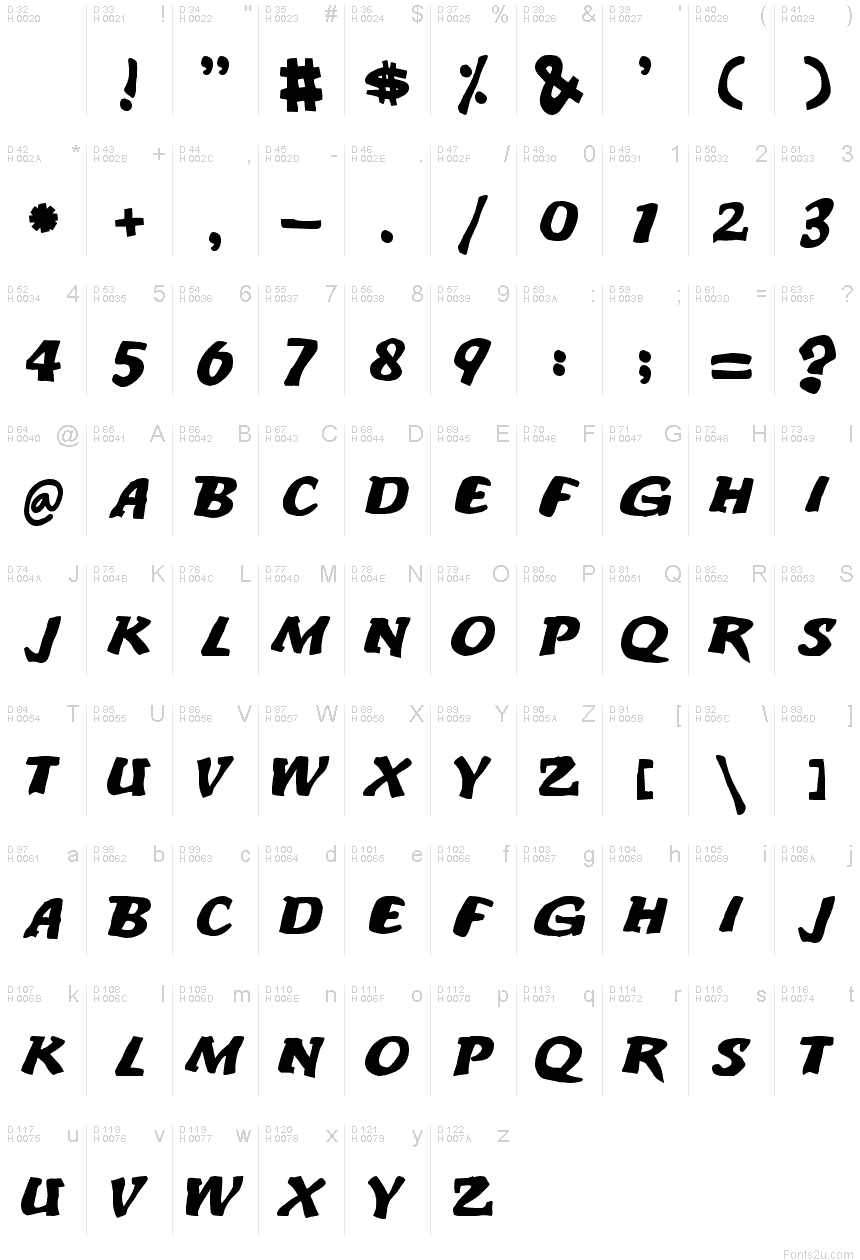
خط An Ode to Noone من تصميم Jakob Fischer المعروف باسم PizzaDude هو خط عرضي مجاني ومشوه يبدو وكأنه انتُزع من ملصق حفلة صاخبة أو غلاف شريط فيديو (VHS) مهترئ. تميل الحروف إلى الأمام بلمسة فرشاة ملطخة، مع منحنيات عريضة وحواف غير منتظمة تمنح الخط طابعاً ملحاً وجامحاً بعض الشيء. تحمل الأشكال طاقة حبرية خام، وكأنها رُسمت على عجل وتُركت لتسيل، مما يضفي على العناوين قوة بصرية يدوية الصنع.
باستخدام An Ode to Noone، يمكنك إضافة طابع جريء ومتمرد مباشرة إلى أغلفة الألبومات، والمجلات، وعناوين أفلام الرعب، وتصاميم علامات التزلج أو ملابس الشارع، وملصقات الفعاليات، وتصاميم وسائل التواصل الاجتماعي. يتألق هذا الخط المجاني عند استخدامه بأحجام كبيرة، حيث يبرز إيقاعه المشوه ووزنه العريض ليفرض حضوره. للحصول على تصميم متوازن، قم بدمجه مع خط بلا زوائد (Sans Serif) نحيف ونظيف للنصوص الأساسية، واترك An Ode to Noone يتولى صياغة الكلمات الأكثر تأثيراً وجرأة في الصفحة.